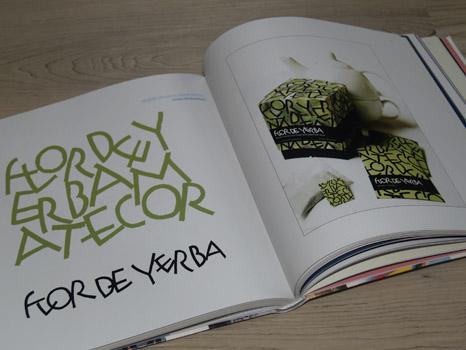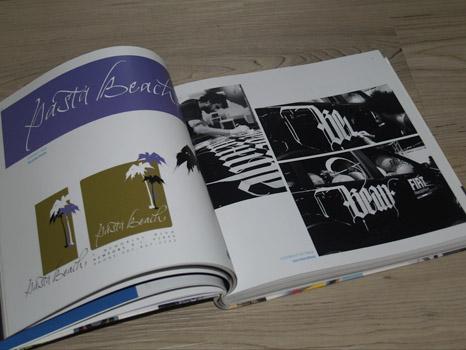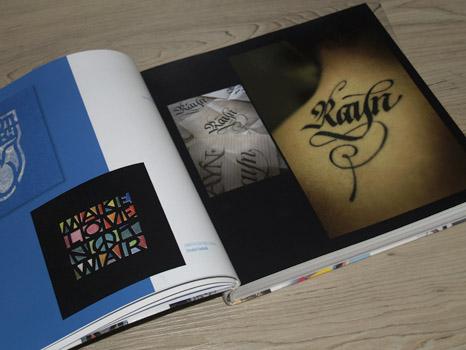
Applied Calligraphy and Graphic Design gibt einen Einblick in die moderne angewandte Kalligrafie. Sortiert nach Einsatzbereichen und Medien werden hier erstklassige Beispiele in den unterschiedlichsten Stilen vorgestellt. Die Bandbreite reicht von klassischer und expressiver Kalligrafie bis zeichnerisch ausgefeilter oder flüchtiger Beschriftung. Zu den gezeigten Künstlern gehören u. a. Massimo Polello, Monica Dengo und Luca Barcelona.
Die Kategorien sind: Grafik, Logos, Werbung, Grußkarten, Videos, Bücher und Magazine, Packaging, Mode, Urban Art, Inneneinrichtung, Objekte und Verschiedenes.